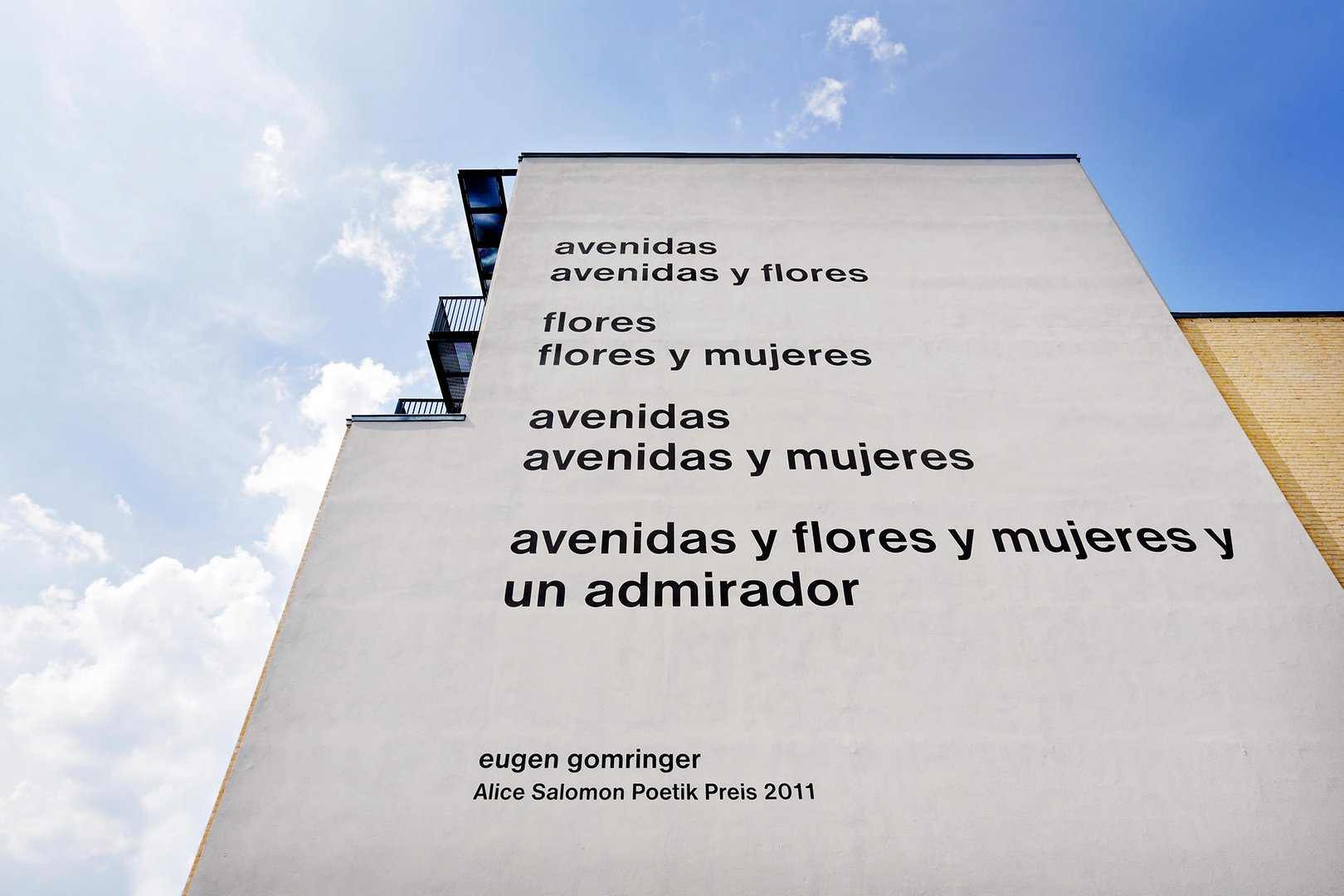
Außergewöhnliche Unterlänge bei y und j
Aufgrund des aktuellen Themas (Übermalen eines angeblich sexisitischen Gedichts an der Hauswand einer Schule), wurde ich gefragt, um welche Schrift es sich handelt. Leider war ich überfordert. Ich würde mich freuen, wenn mir jemand die Antwort geben kann. Es grüßt euch Monroe!
Das ist eine Helvetica Bold.